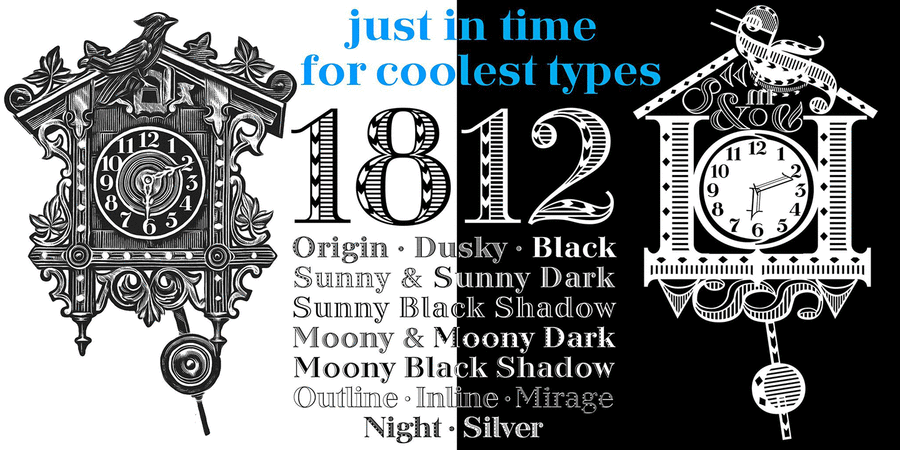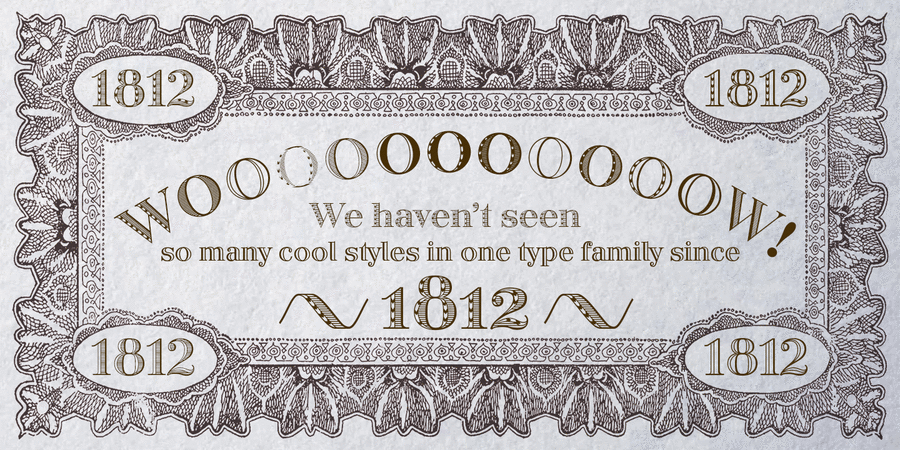
Ця гарнітура є історичною реконструкцією та подальшим розвитком шрифту «1812» від Ливарні Йосипа Лемана (Санкт-Петербург). Він був створений до сторіччя французького вторгнення в Росію, відомого в Росії як Вітчизняна Війна 1812 року, за мотивами декоративних гравірованих написів та орнаментованих шрифтів того часу, ймовірно художником Олександром Бенуа. Його використовували в основному для прикраси розкішних елегантних видань. Пізніше, у 1917 році, цей шрифт був використаний на банкнотах Тимчасового Уряду Росії. За радянських часів «1812» виявився одним з небагатьох шрифтів, включених у перший радянський шрифтової стандарт ОСТ 1337. Він випускався для ручного набору до початку 1990-х років. Цей шрифт можна було побачити на радянських документах, плакатах і навіть на авіаквитках. Розробка цифрової версії почалася в 2010 році. До новлї версії були додані рядкові літери та альтернативні символи. Повністю підтримується розширена латинка й кирилиця. Шрифт був перетворений на сімейство з 14 декоративних накреслень, які можуть поліпшити будь-який дизайн, надавши йому святкового та елегантного, але водночас ностальгічного вигляду. Незважаючи на свій декоративний характер, «1812» відмінно читається в невеличких текстових блоках завдяки своїй класичній формі й ретельному розташуванню знаків. Шрифт розробили Віктор Харик і Костянтин Головченко у 2020 році.
Хіт 1900-х Близький історичний оригінал:
Асоціації з сімейством шрифтів 1812 YearОсобистість і характер гарнітури:
класичний, важливий, помітний, яскравий, серйозний, авторитетний, старовинний, історичний, гордий, активний, вишуканий, оригінальний, багатий, аристократичний, салонний, урочистий, дзвінкий, благородний, майстерний, художній, музичний, красивий, прекрасний, блискучий, розкішний, дорогий, елітний, якісний, культурний, естетичний, знаменитий, дорогоцінний, добірний, ефектний, гострий, ювелірний, витончений, театральний, творчий, химерний, святковий, ажурний, характерний, екстравагантний, артистичний, виразний, претензійний, естетський, цікавий, тонкий, легкий, прозорий, скляний, освічений, гламурний, золотий, сексуальний, пристрасний, драматичний, модний, комільфо, переконливий, глянцевий
банкнота, музей, карти, музика, розкіш, театр, опера, готель, мистецтво, література, вино, ресторан, срібло, прикраса, ювелір, чай, годинник, подарунки, свято, реклама, інтер'єр, сувенір, шоколад, кафе, десерт, антикваріат, преміум, цукерки, гроші, цінні папери, вечір, пейзаж, люкс, банк, захід сонця, детектив, мафія, монета, косметика, мода, золото, перукарня, парфумерія, драма, тату, татуювання, парфуми, Інстаграм, бутік, гламур, костюм Гарнітура має ознаки стилів: